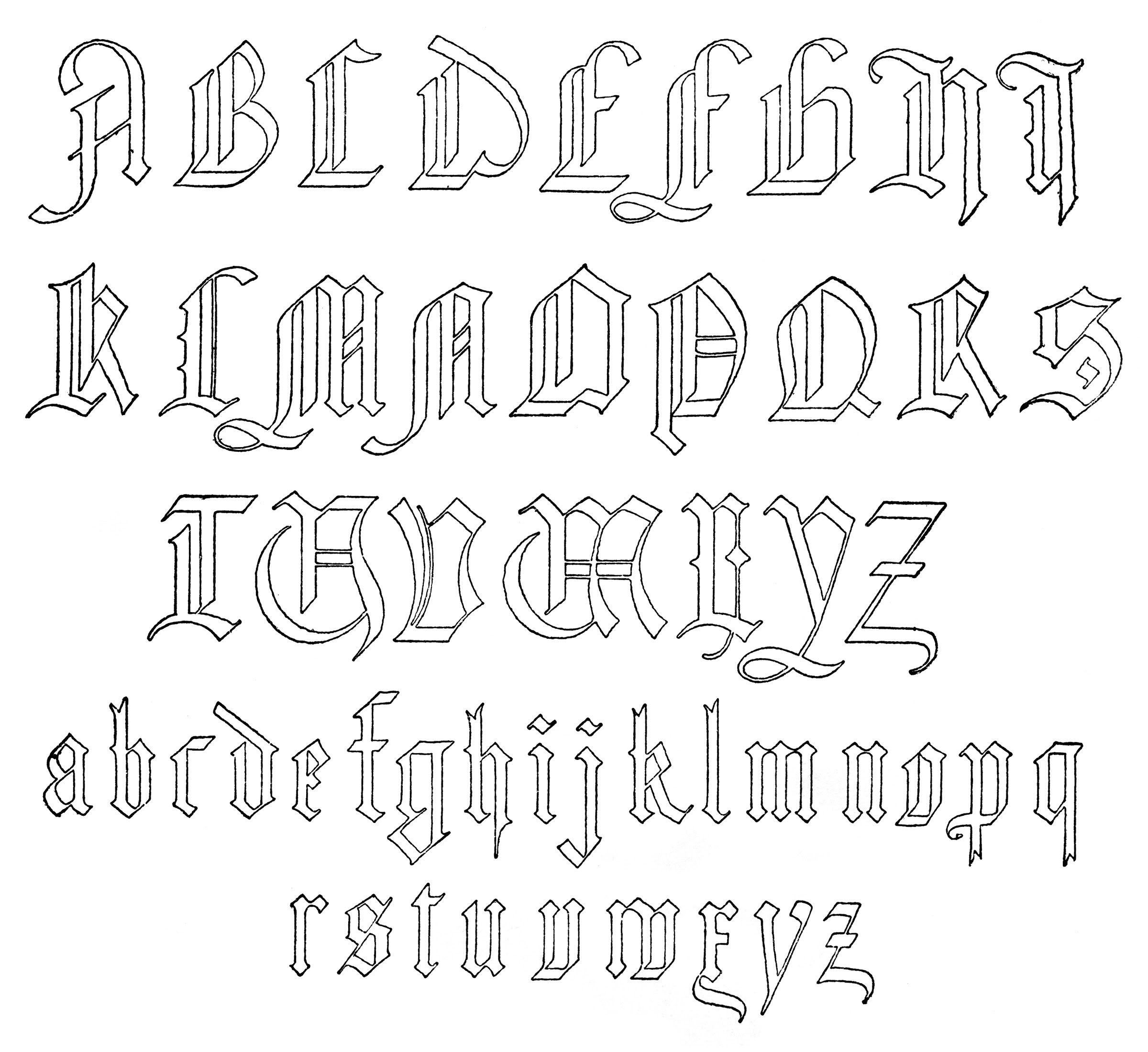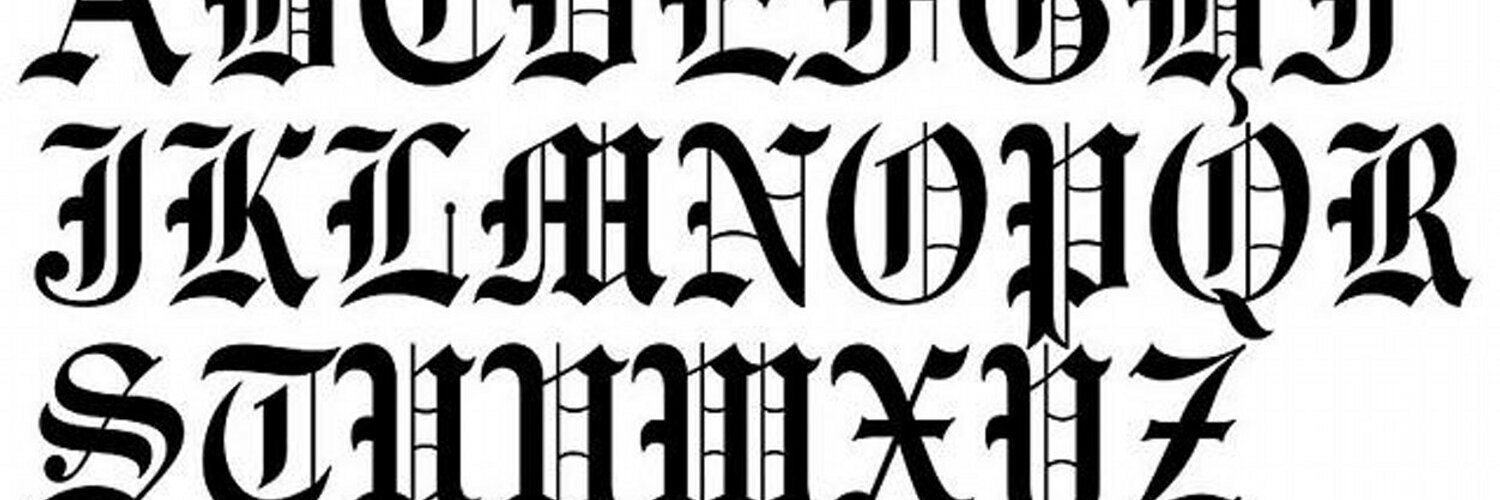
Шрифт готический русский для фотошопа: 25 русских шрифтов с стиле «Готика»
Каковы преимущества профессионально созданного веб-шрифта?
— поддержка языков и возможность настройки письма;— несколько вариантов стилей и начертаний;
— подобранные кернинги.
В нашей коллекции веб-шрифтов мы предлагаем шрифты для самых разных сайтов — от корпоративных проектов до ресурсов развлекательной тематики.
Как правильно подобрать шрифт для интернет-проекта?
Главное требование, которое выдвигается к любому шрифту — это читаемость. Вы создаете сайты для людей, которые приходят на ваши страницы за информацией. Чтобы обеспечить им комфорт в потреблении контента, выбирайте только качественные наборы шрифтов. Русские шрифты скачать важно для аудитории, родной язык которой русский.
Однако не стоит использовать на одном веб-проекте слишком много шрифтов, чтобы не путать и не рассеивать внимание читателей. Оптимальное количество используемых на сайте шрифтов — 2. К примеру, один из них можно использовать при создании заголовков, а другой — для публикации основного контента. Так проекта будет выглядеть более привлекательным и целостным, а пользователи смогут легко отличать основной контент от второстепенного.Шрифты бывают:
— с засечками (как правило, отличаются очень хорошей читабельностью, придают сайту элегантности и утонченности).— с прямоугольными засечками (если вам необходим стильный сайт, используйте этот тип шрифтов на его страницах).
— рукописные (придают индивидуальности и выглядят так, как будто текст написан от руки).
— прописные (шрифты могут использоваться в качестве декоративных вставок. Не рекомендуется выбирать их в качестве основного оформления для сайта).
— готические (еще один декоративный шрифт, который можно использовать, к примеру, на сайтах старинных вещей и магазинов антиквариата).
На самом деле, хороших шрифтов огромное количество. И еще больше вариантов их использования и совмещения. В качестве основного шрифта для сайта, к правило, выбирают стильные шрифты с засечками — так можно не сомневаться в читабельности проекта. Стоит обращать внимание на стили шрифтов, чтобы в полной мере использовать их на своем сайте.
Высокое качество
Наборы шрифтов из нашей коллекции удивят вас вариативностью символов и сделают текстовый контент 100% уникальным. Также в некоторые шрифты включены лигатуры, чтобы ваши проекты выглядели еще более аутентично. Для иностранных пользователей предусмотрены разные языковые версии.Доступные цены
Мы уверены, что наша ценовая политика вас приятно удивит. Кроме того, вы можете дождаться распродажи и приобрести лучшие наборы шрифтов по низкой цене! Красивые шрифты скачать просто, если они сделаны специалистами TemplateMonster.
18 крутых шрифтов от TemplateMonster для типографики
Когда создаешь сайт, больше внимания уделяется дизайну, цветам, расположению контента, но мало кто задумывается про выбор шрифтов. Большинство дизайнеров используют шрифты Google, и, обычно, их вполне хватает для оформления текстов обычных сайтов. Но, если речь идет о специфических ресурсах, например, магазин этнической одежды, то заурядными шрифтами тут не отделаешься!
В таких ситуациях приходится искать специальный шрифт для Фотошопа, который соответствуют типу бренда и переделывать все снова и снова. Поэтому важно не пренебрегать важностью выбора правильных шрифтов для своего проекта. Ознакомьтесь с новыми шрифтами, в том числе и для Фотошопа, которые помогут вам создавать привлекательные тексты.
23. Hansief
Винтажный шрифт — ждёт, пока вы его скачаете, тут.
24. Вечер вторника
25. Внимательно
26. Рустико
27. Элерон
28. Большой Джон / Тонкий Джо